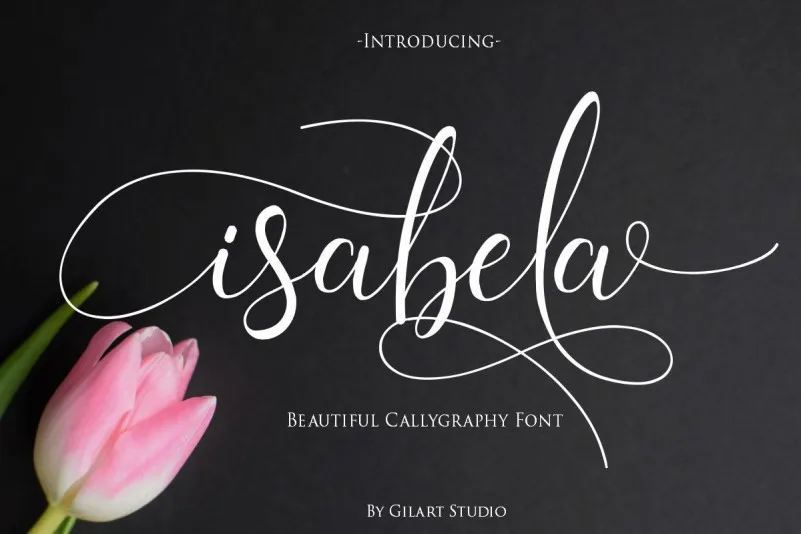
Isabela Calligraphy Font
A Isabela Calligraphy Font é uma nova opção moderna para os amantes do tipoográfico. Ela traz swashes únicos que permitem criar belos textos de forma simples e rápida. Esta fonte possui muitas alternativas de estilo set, com as quais você pode escolher o melhor para seu design. Introduzida pelo designer zziplex, a Isabela é um tipo romântico e autografado, repleto de swashes impressionantes e selvagens. Idealmente projetada para ser usada em logotipos e outros formatos formais como cartões de visita, selos, logos, revistas, livros, cartas casamentos, embalagens, moda, maquiagem, material de escritório, novelas ou rótulos. Sua utilização pode levar a qualquer finalidade de marketing. Com uma paleta única de swashes e o equilíbrio entre elegância e naturalismo, esta font é perfeita para aqueles que querem dar um toque personalizado aos seus projetos, seja por meio de seu estilo autografado ou pelo brilho das suas linhas suaves. Uma escolha versátil para designers, anúncios e criativos que valorizam tanto a elegância quanto o instinto humano no design.